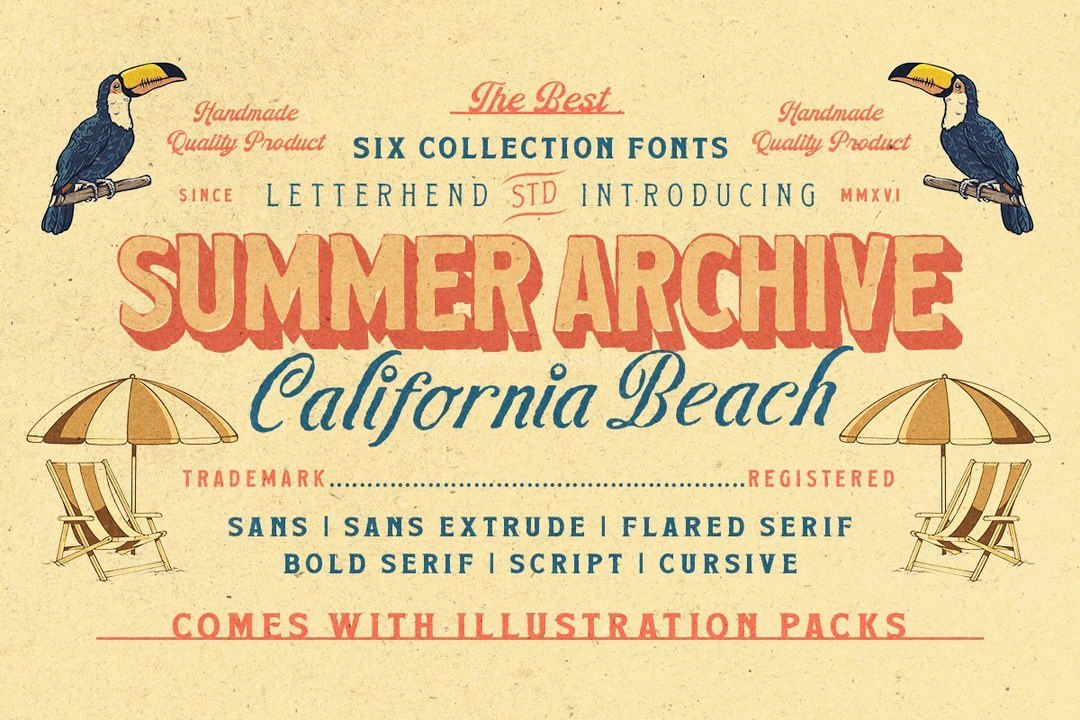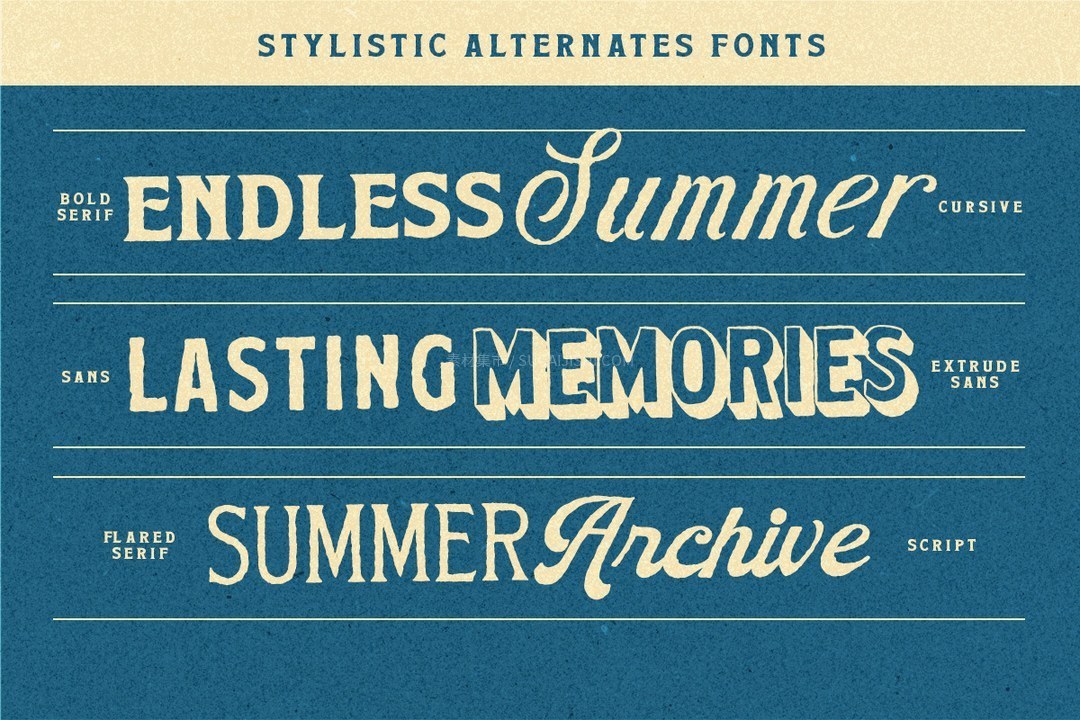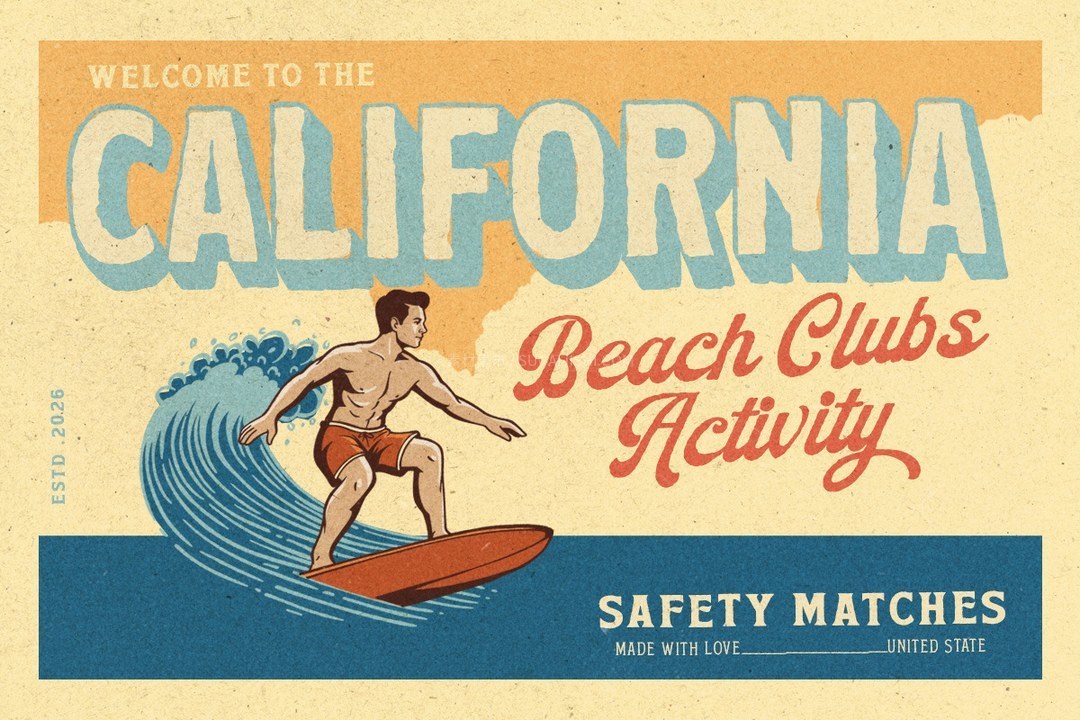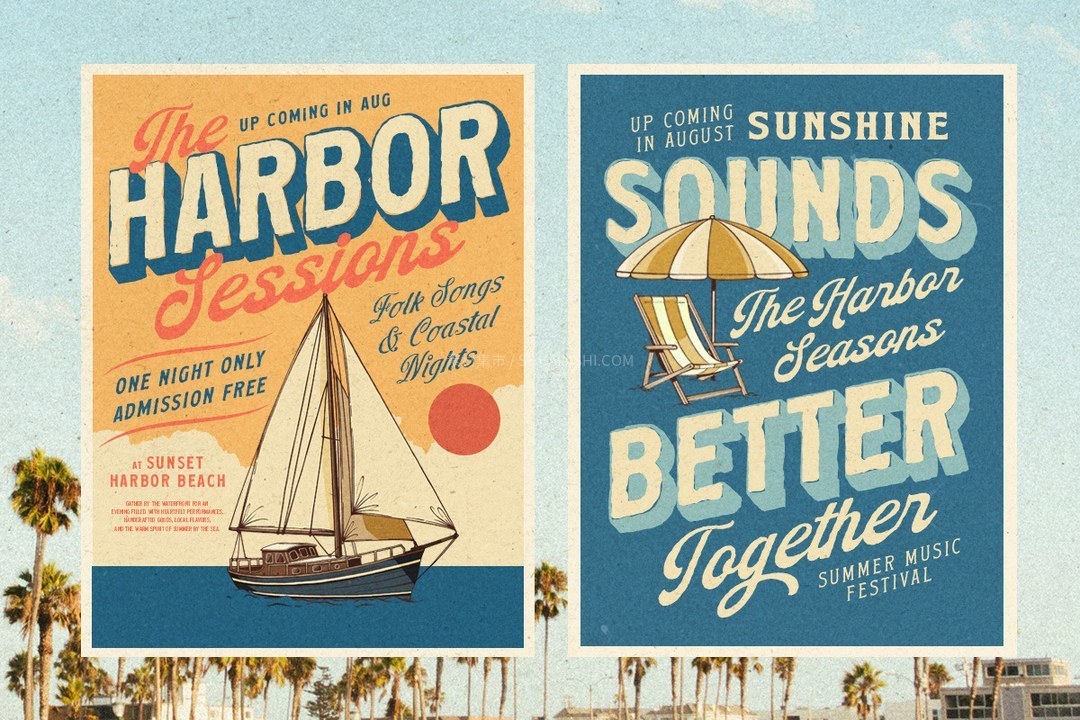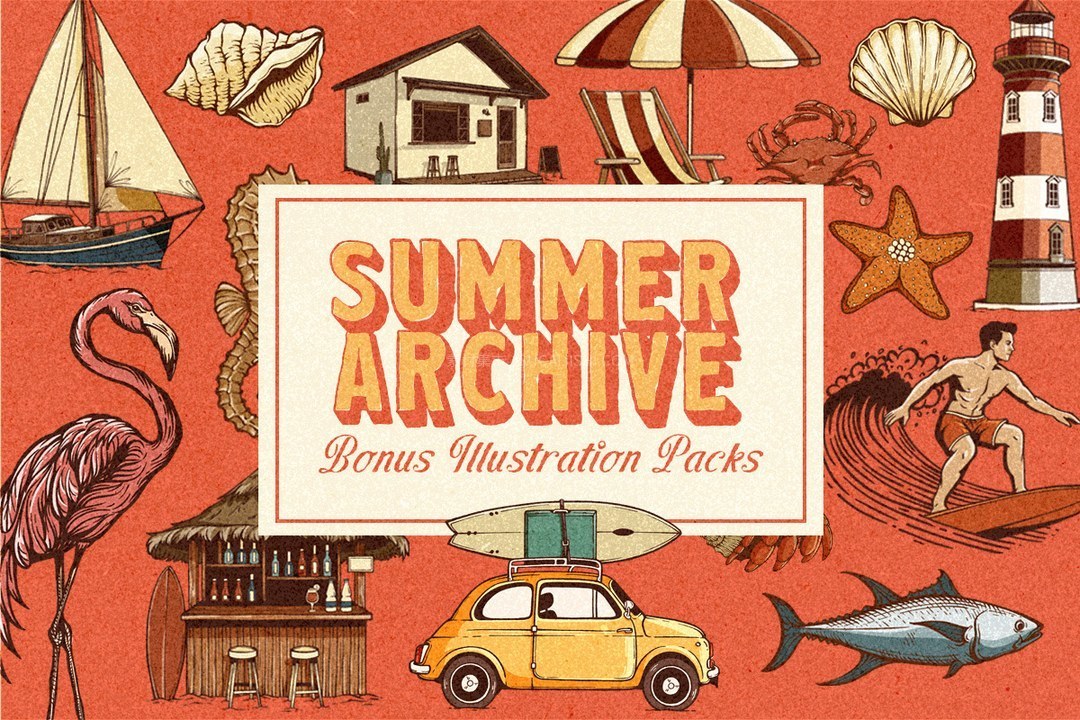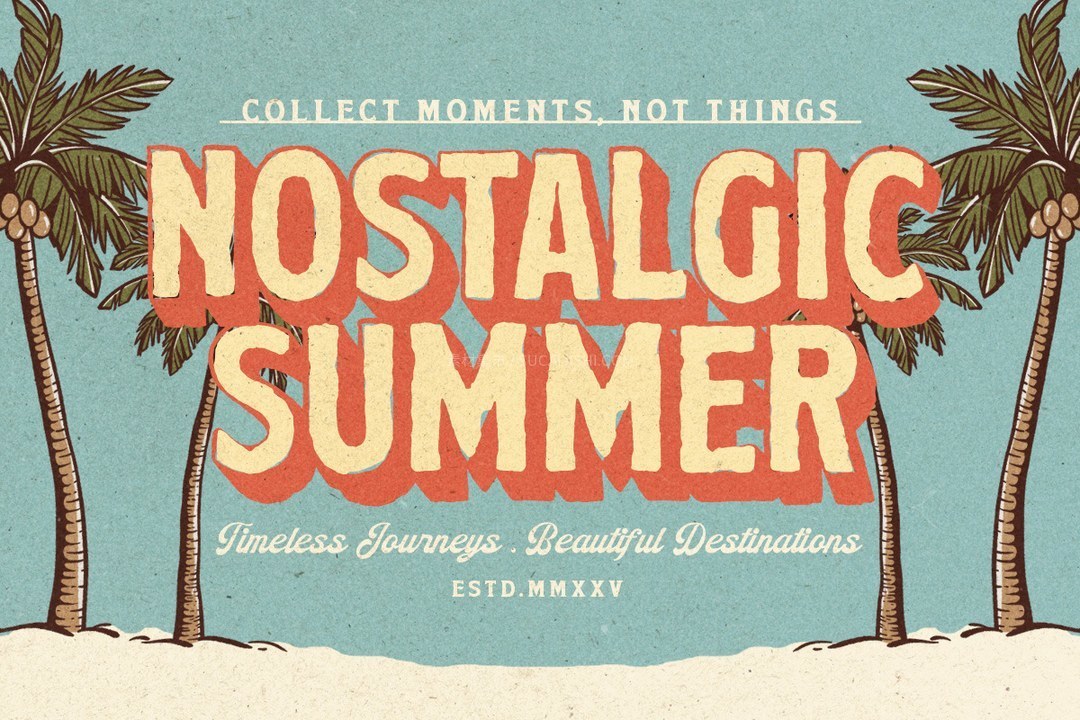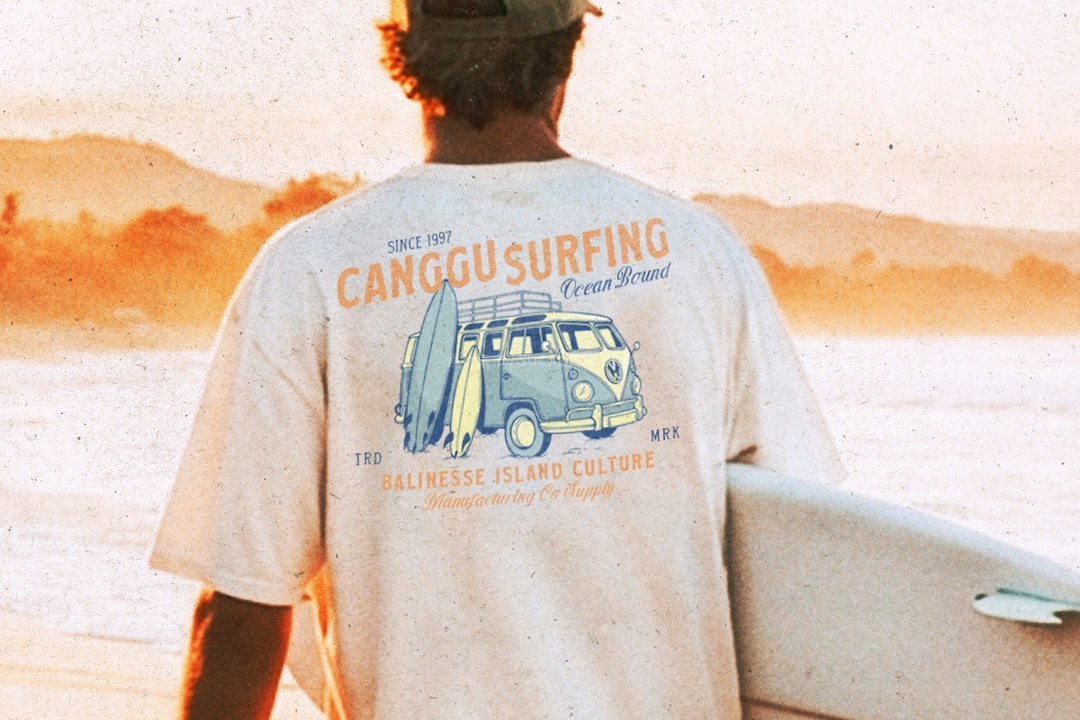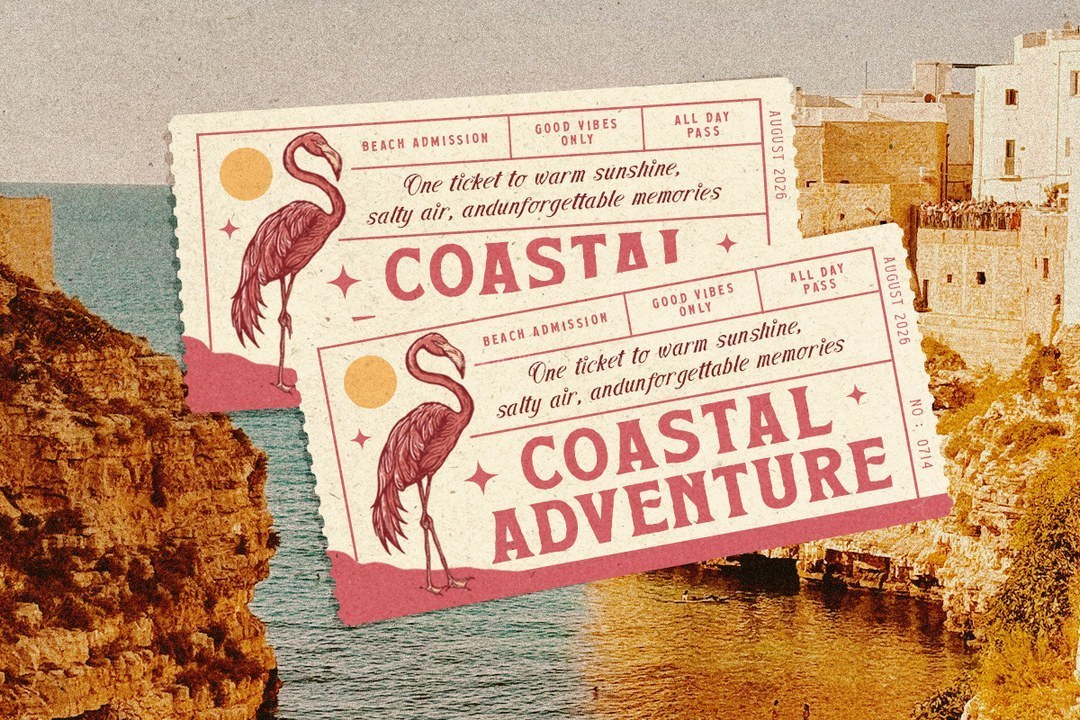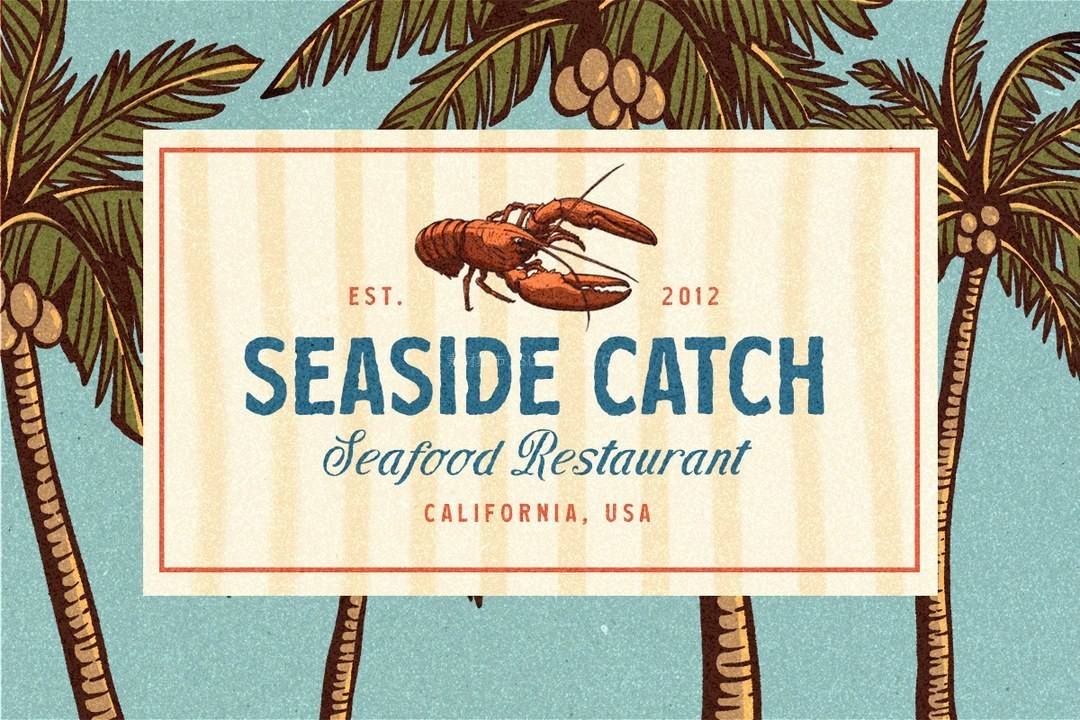
Summer Archive复古夏日典藏字体系列
Summer Archive Font Collection 是一套让你爱不释手的字体系列。夏日典藏系列将海边的悠闲时光、复古明信片和经典的加州海滩风情完美融合。该系列包含六种协调的字体风格——粗衬线体、喇叭形衬线体、无衬线体、凸形无衬线体、手写体和草书体——复古风格十足,助你轻松打造极具特色的海报、品牌标识、包装和标牌。